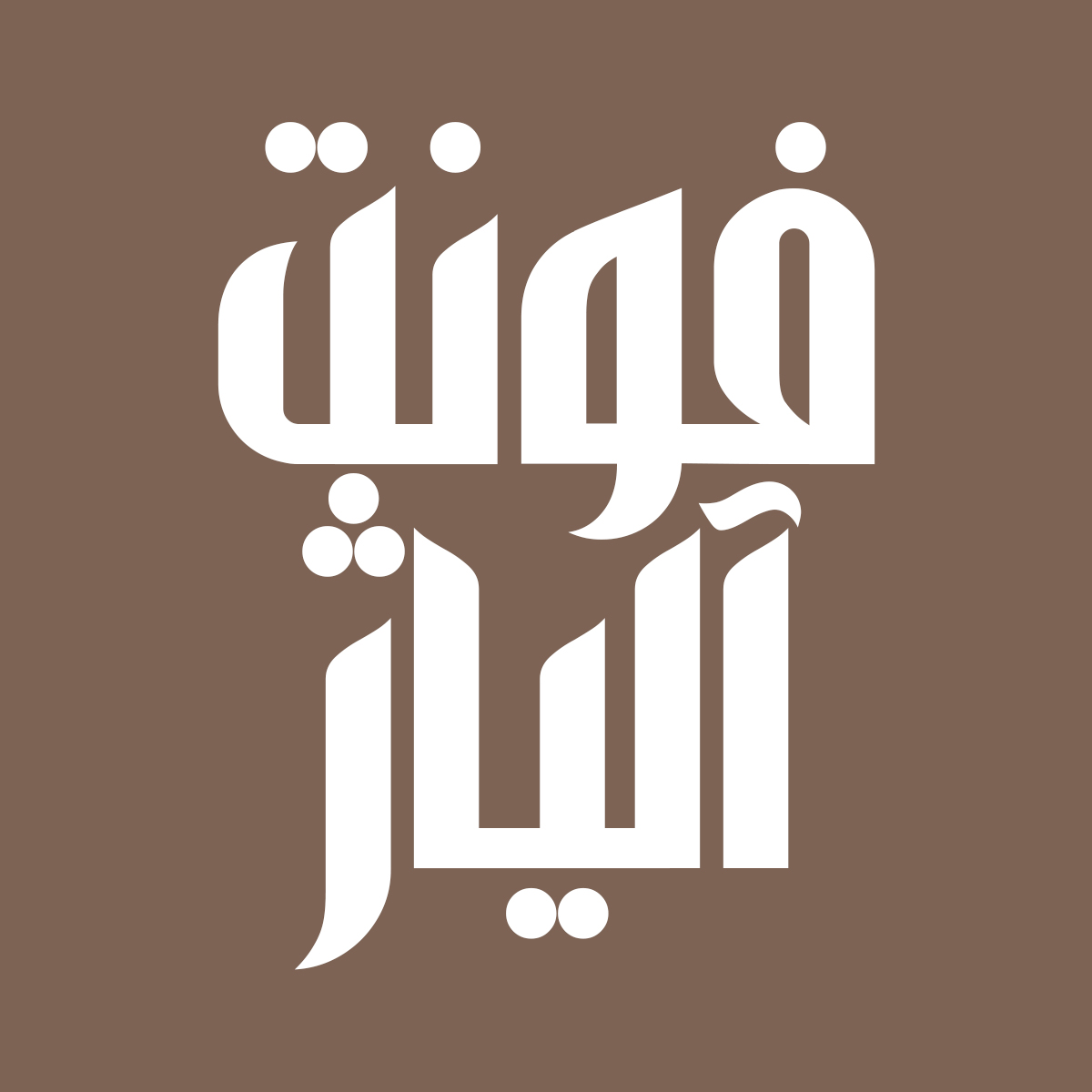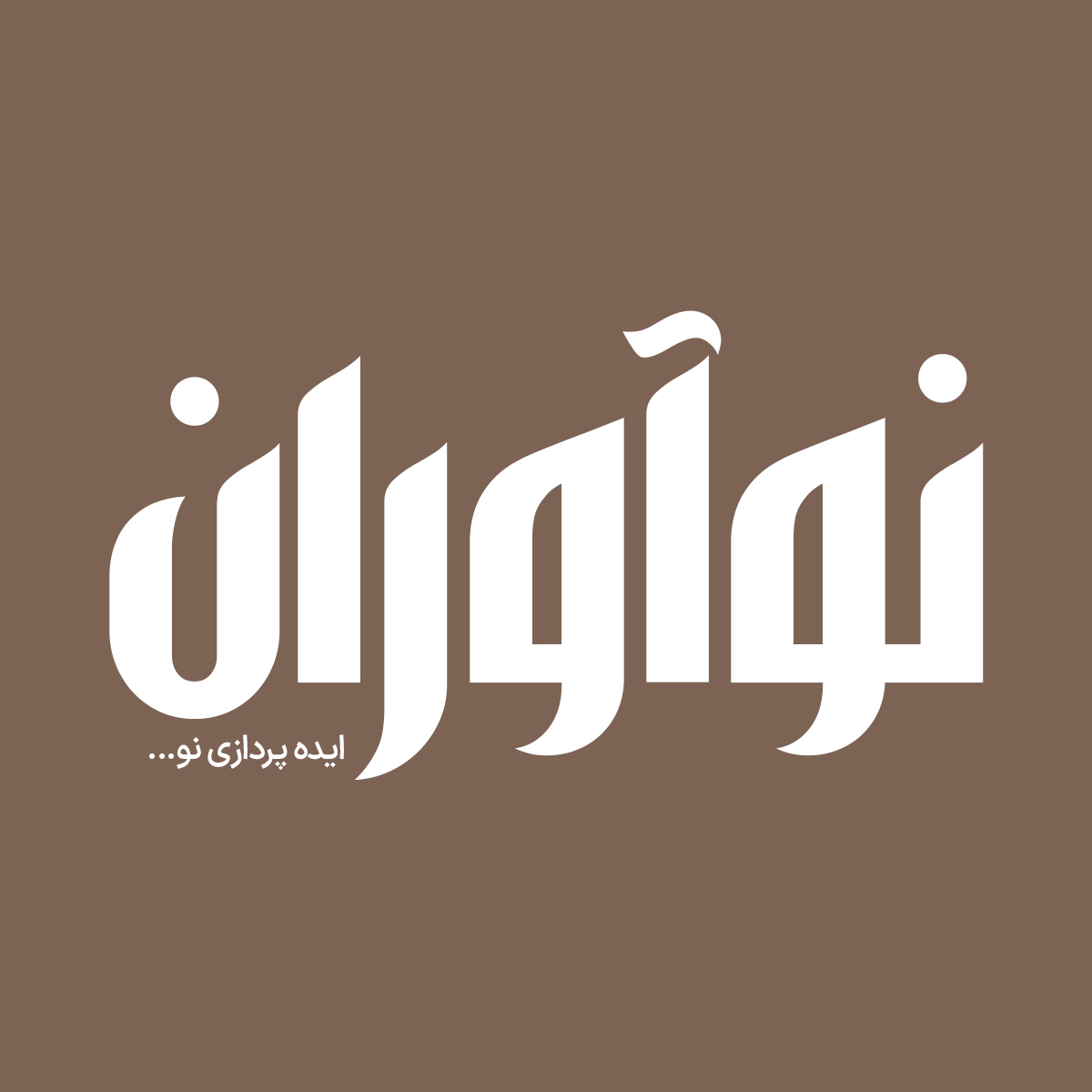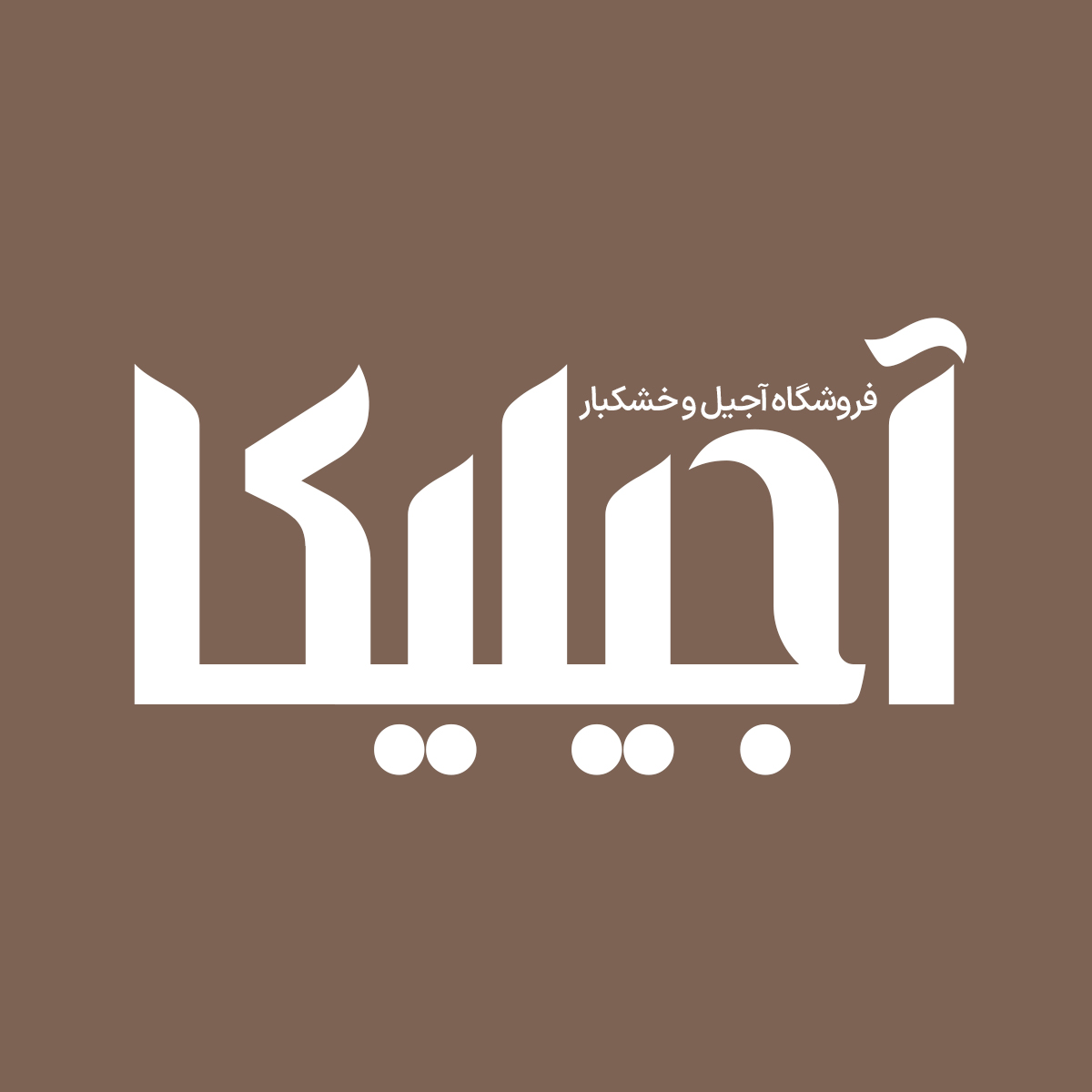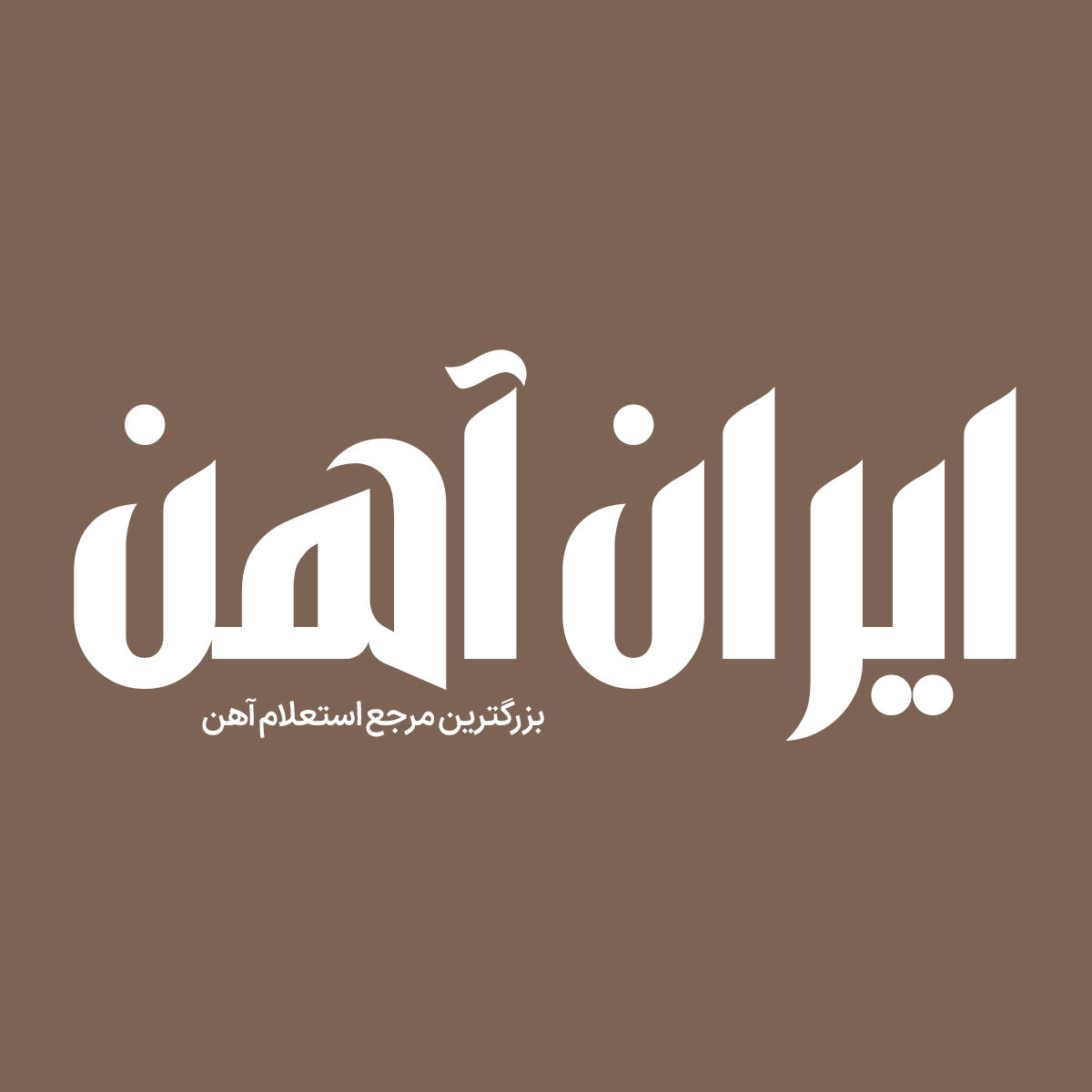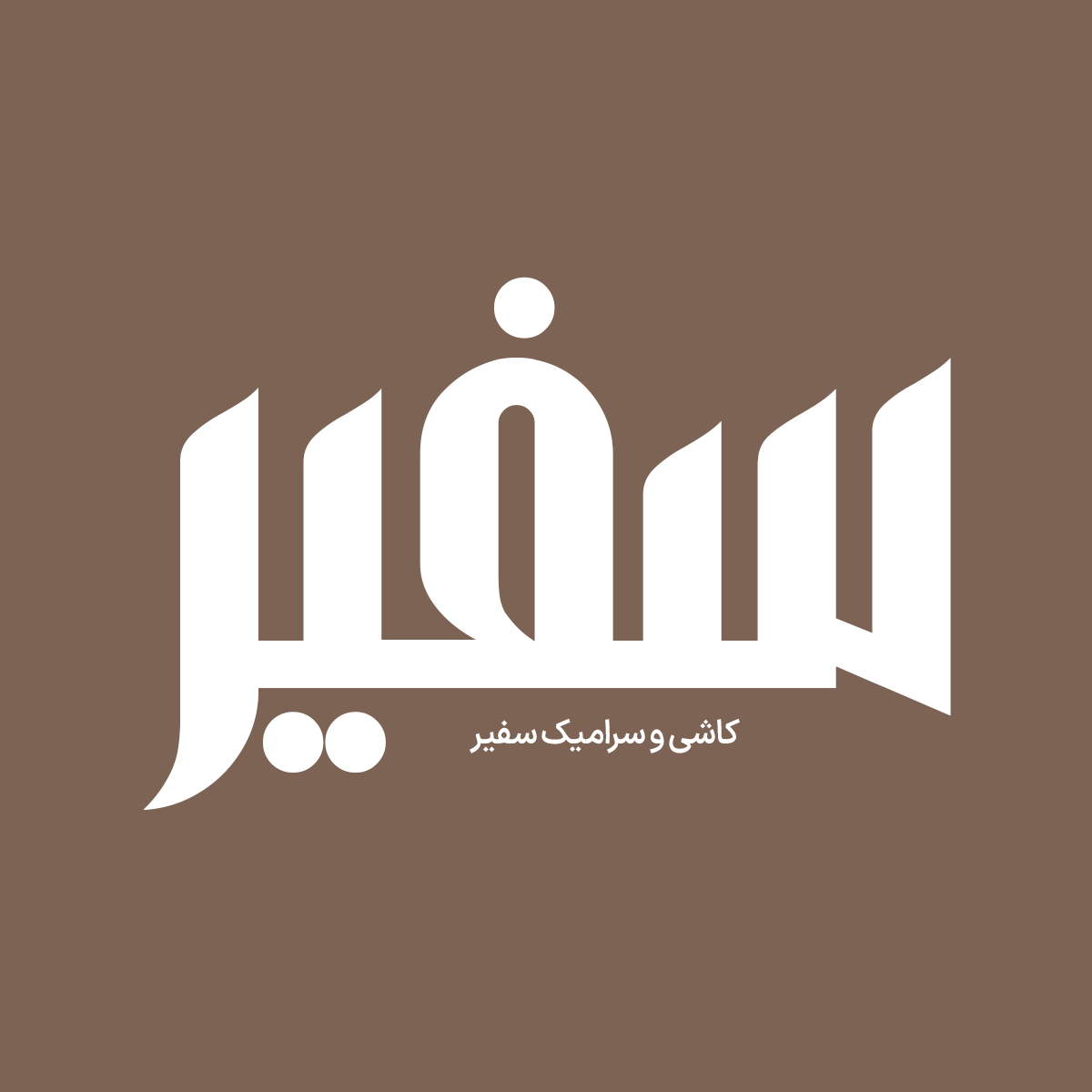
فونت فارسی آلیاژ Aliyazh Font
فونت فارسی آلیاژ از دسته فونت های کوفی است. از این فونت می توان برای طراحی لوگو، طراحی اسم، دیوار نوشتههای هنری و مذهبی، طراحی بنر،…
فونت فارسی آلیاژ از دسته فونت های کوفی است. از این فونت می توان برای طراحی لوگو، طراحی اسم، دیوار نوشتههای هنری و مذهبی، طراحی بنر، طراحی پوستر و غیره استفاده کرد و این به جهت شکستگیها و انحناهای متعادل، همنشینی روان حروف در کنار هم، حجم دهی بالا و اتصالات مختلف است. از آنجایی که فونتهای عربی فاقد حروف “گچ پژ” هستند و مشکلاتی در تایپ حروف “ک” و “ی” دارند در فونت آلیاژ حروف “گچ پژ” و همچنین اعداد فارسی اضافه شده است و حروف “ج، چ،ح، خ، د، ذ، ع، غ و…” بازطراحی و بهینه شده اند تا بتوانید تمامی متن فارسی را به وسیله این فونت تایپ کنید. در ادامه برای شما نمونه تایپ های این محصول حرفه ای رو آماده کردیم که میتونید مشاهده کنید.
پیشنمایش و نمونه تایپ های فونت آلیاژ